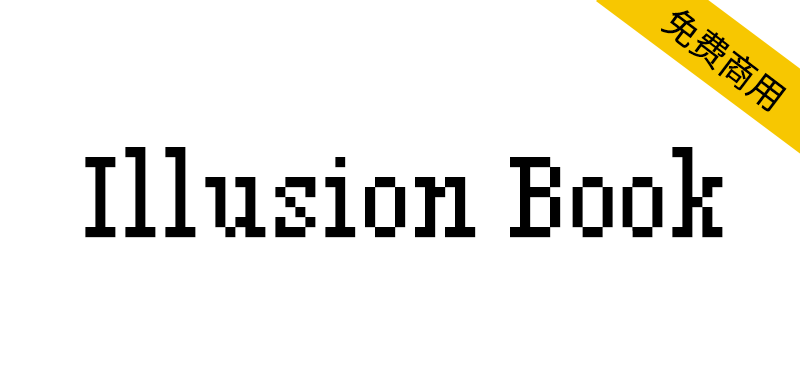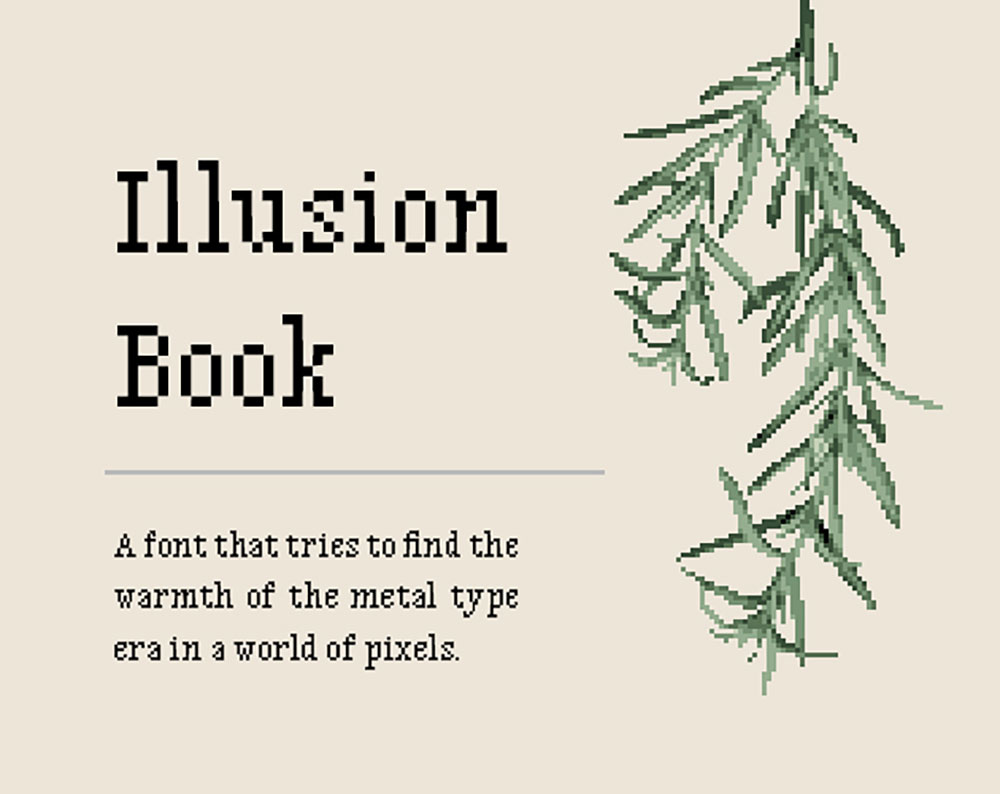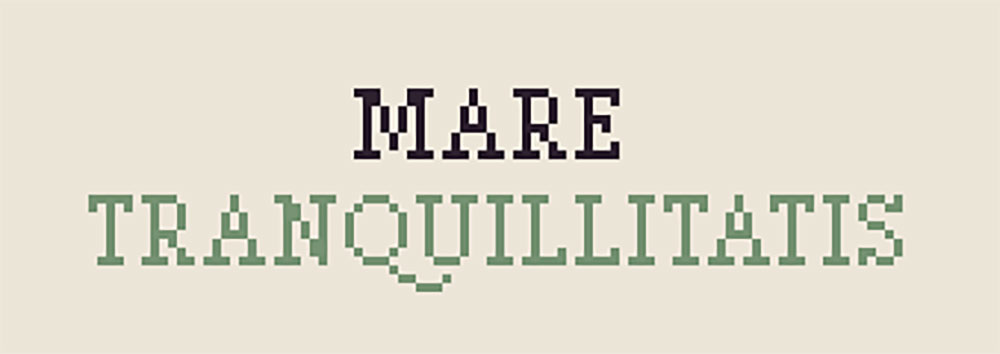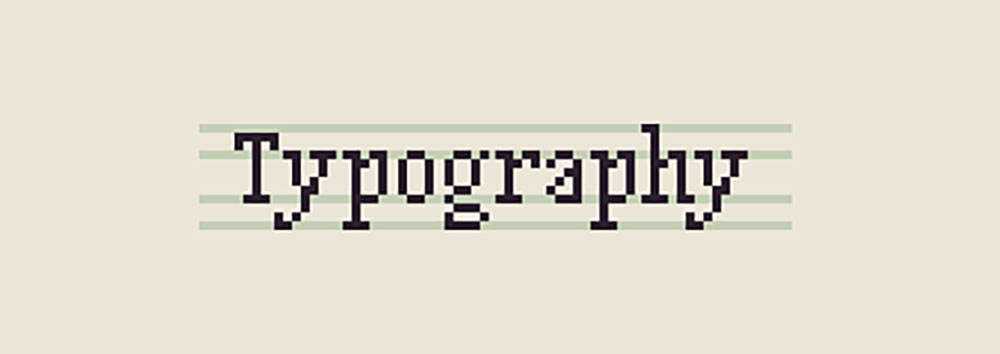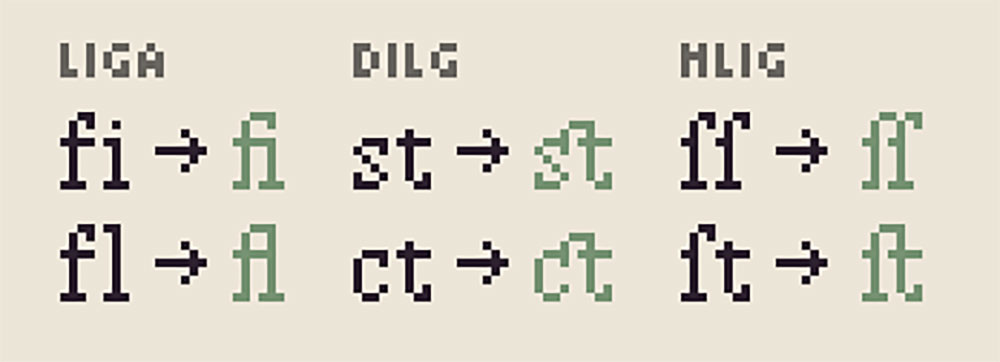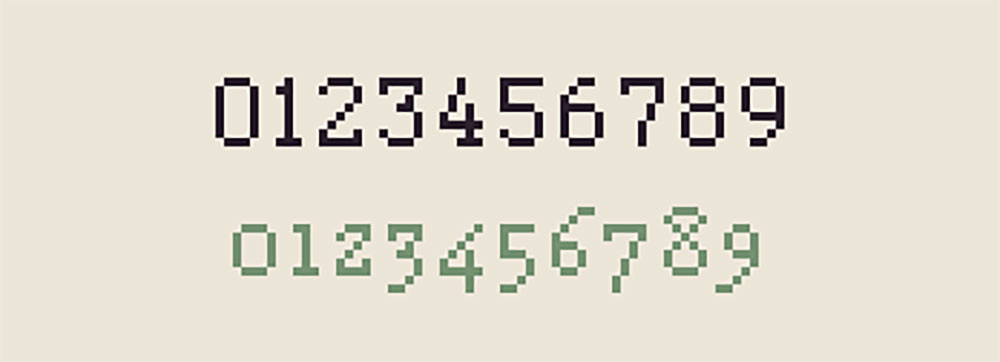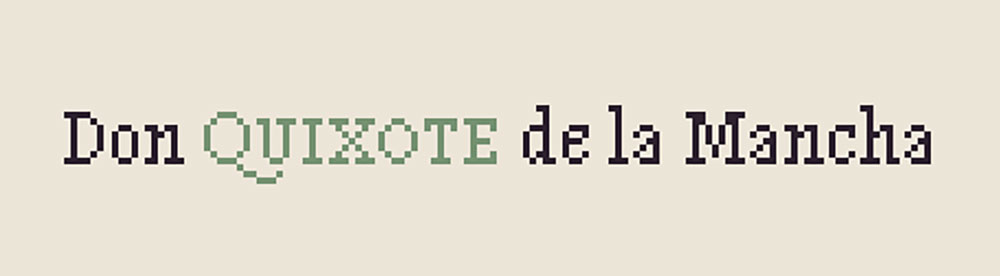
Illusion Book(幻象像素书体)是一款尝试在像素世界中寻铅字时代的温润的字体,经过半年多的设计与打磨后,完成了以西文为主的支持。目前其他例如中日韩的字符集仍在开发中。
该字体的 UPM 值为 1200。若想取得最佳显示效果,字号应基于 12px 的大小进行整数倍的缩放。
请注意,由于本字体在字距调整时并未完全采用整数倍单元格大小的数值,这可能导致在某些情况下字体不能正确地渲染。在允许的情况下,请关闭任何的抗锯齿设置以及过滤模式,并将字距微调和追踪皆设为 0。
设计理念是希望能够在像素风格上,展现衬线体所特有的优雅,同时还要有高可读性,适用于大段文本。然而,这款字体最显著的变化便是缩小了字怀。小巧的字怀使文字的排列更加紧致,灰度更加均匀,同时不失节奏感。
字形也并未设计成等宽的样式,因为有些字母强行拉宽会显得十分拖沓;而有的强行压缩则又会拥挤不堪。在设计时大量参考了传统的旧式字体,例如罗马大写体,对每个大写字母的宽度进行了分类,并以此为依据进行设计。
在比例上,整套字体基于 12px 的尺寸进行设计。升部的高度为 9px,降部的高度为 3px。大写字母的高度被特意设计成比升部矮一个像素;而 6px 高的小写字母既不显得过于狭长,也不矮胖。
高级排版特性:虽然看上去是像素的,但并不是老旧的像素字体格式,所有的「像素」其实都是由矢量轮廓描摹出来的,除此之外,它还配备了丰富的高级排版武器,即 OpenType 特性。在专业的平面设计和排版软件(比如 Adobe InDesign 和 Illustrator)以及网页开发中,它能够让文字以更加灵活的方式呈现。比如,按照西方排版惯例,自动将一些字母连写的合字(ligature)功能:
以及为了配合小写字母的旧式数字(old-style figures):
还有小型大写字母(small capitals):
除了字形以外,字符间距也经过了仔细推敲。为了美观,在制作这款字体时毅然放弃了以整数倍单元格宽度进行调整的思路,就是为了避免在某些情况下会出现「不调整看上去不太对劲,调整了又更不对劲」的尴尬地步。以 1/4 单元格宽度为基础,对大量的字偶对进行了手动微调。